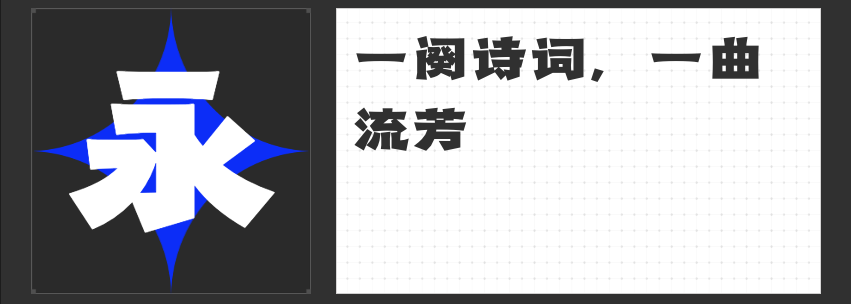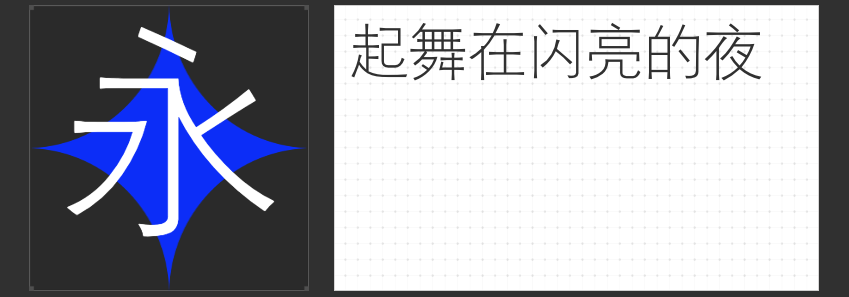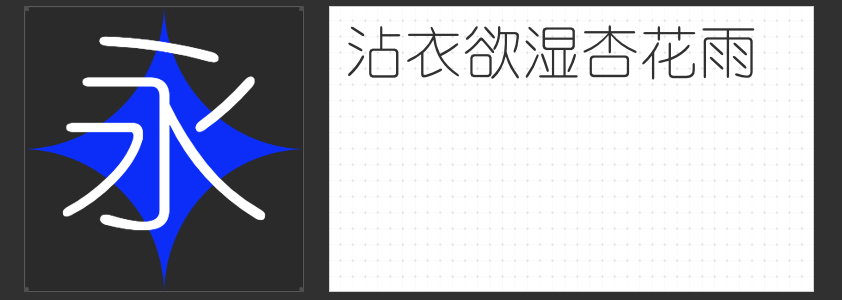
【字体推荐】打造悬疑氛围——四款精选字体助力案情解说视频
悬疑案讲解视频因其扣人心弦的情节和紧张刺激的氛围而深受观众喜爱。为了增强视频的吸引力并提升整体观感,选择合适的字体对于制作来说至关重要。今天,我们将推荐四款适合用于悬疑案讲解视频的字体,帮助你更好地传达故事内容,为观众带来沉浸式的观看体验。
1.励字粗圆简繁
在视频封面和视频内介绍的大字部分,一款醒目且具有冲击力的字体能够迅速抓住观众的眼球。“励字粗圆简繁”以其独特的粗圆设计,为悬疑案讲解视频提供了极佳的视觉效果。这种字体既简洁又不失力量感,能够在短时间内引起观众的好奇心,促使他们点击观看。无论是案件名称还是关键信息的提示,“励字粗圆简繁”都能让信息一目了然,加深观众的第一印象。
2.造字侠热辣隶简
对于追求复古风格的悬疑视频而言,“造字侠热辣隶简”是一个非常合适的选择。这款字体融合了传统隶书的特点与现代设计感,不仅能够营造出一种古典神秘的氛围,还能够为视频封面增添一份独特的历史韵味。如果你的视频内容涉及古老的谜团或是经典的侦探故事,那么“造字侠热辣隶简”将会是完美的搭档,带领观众穿越时空,探索未知的秘密。
3.励字细黑简
在悬疑案讲解视频中,字幕部分同样重要,它需要清晰易读,以便观众能够轻松跟随剧情的发展。“励字细黑简”以其简洁大方的设计,成为了字幕部分的理想之选。这种字体的笔画细腻,结构紧凑,即使在快速播放的情况下也能够保持良好的可读性。无论是旁白的解说还是对话的呈现,“励字细黑简”都能确保信息准确无误地传达给观众,避免因字体设计不当而分散观众的注意力。
4.励字细圆简繁
除了以上的几款字体,“励字细圆简繁”也是字幕部分的一个不错的选择。这款字体在保持清晰度的同时,还带有一丝柔和的曲线美,能够为紧张的剧情增添几分柔和感。这种设计不仅能够减少长时间观看的视觉疲劳,还能让整个视频显得更加精致。如果想要在保证字幕易读性的基础上,增加一些设计感,“励字细圆简繁”将是你的不二之选。
综上所述,这四款字体各有特色,能够从不同的角度增强悬疑案讲解视频的表现力。通过精心挑选和合理搭配这些字体,你将能够为观众带来一场视觉与心理双重享受的悬疑盛宴。希望今天的推荐能够为你的创作之路提供更多灵感和支持!